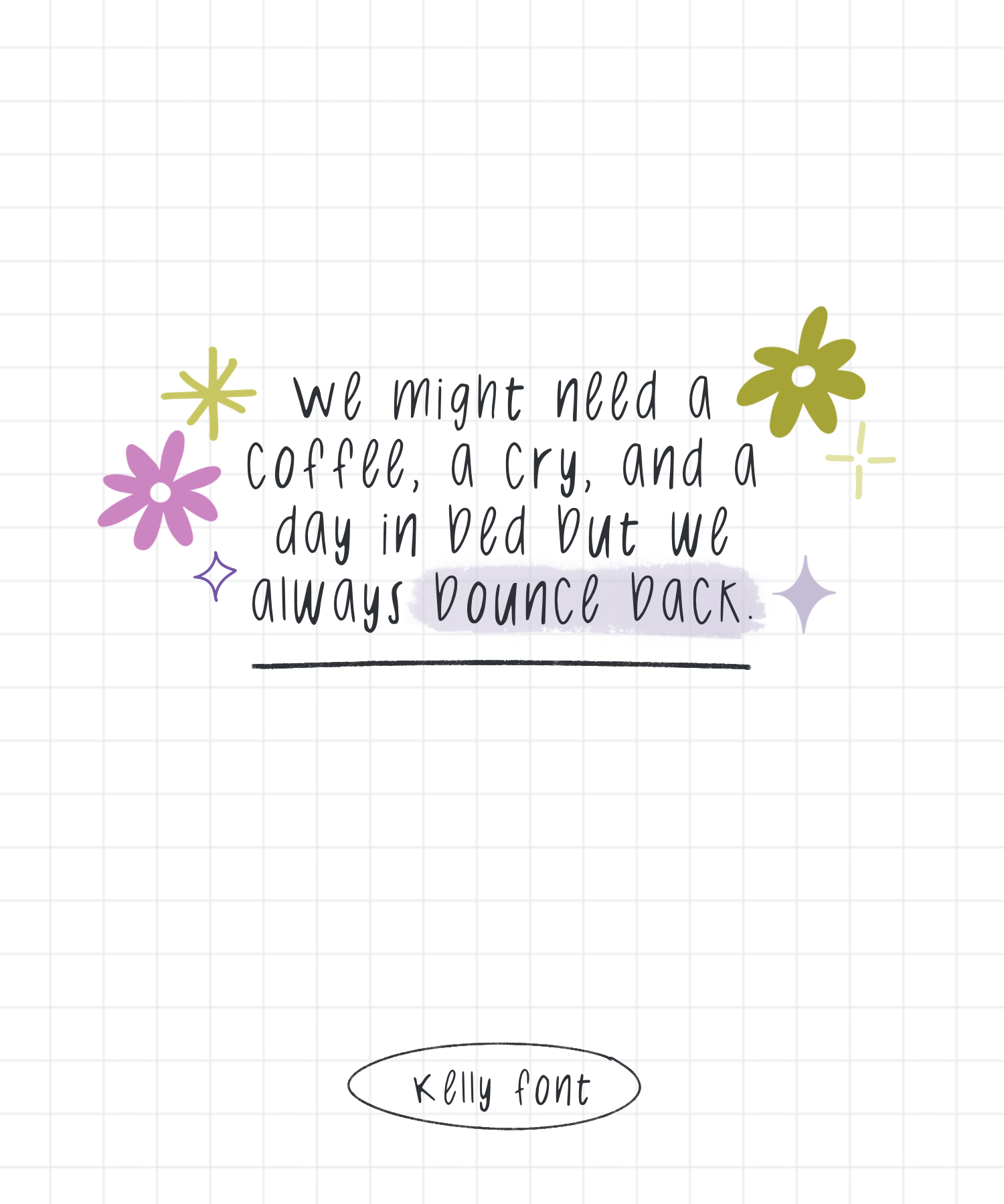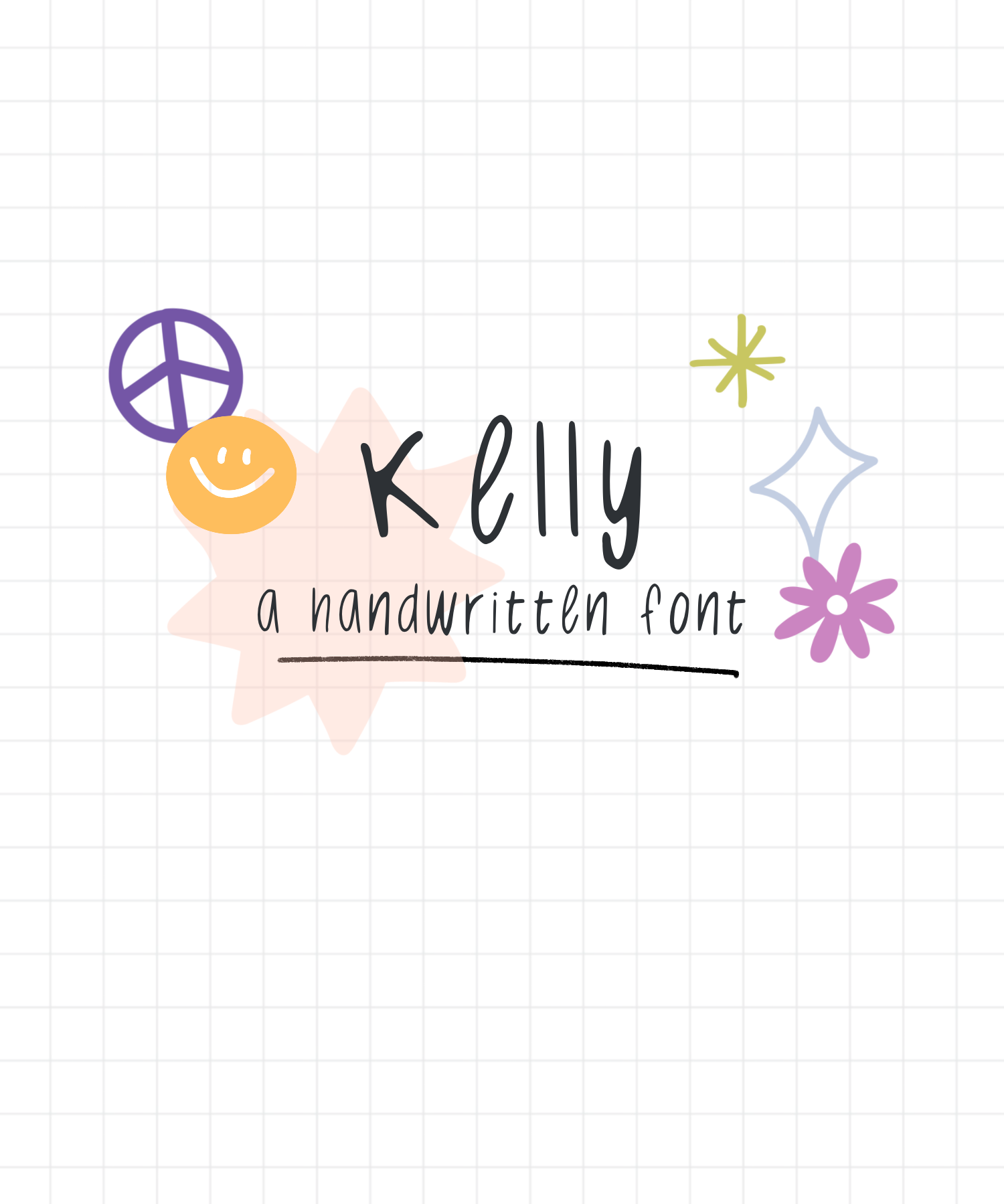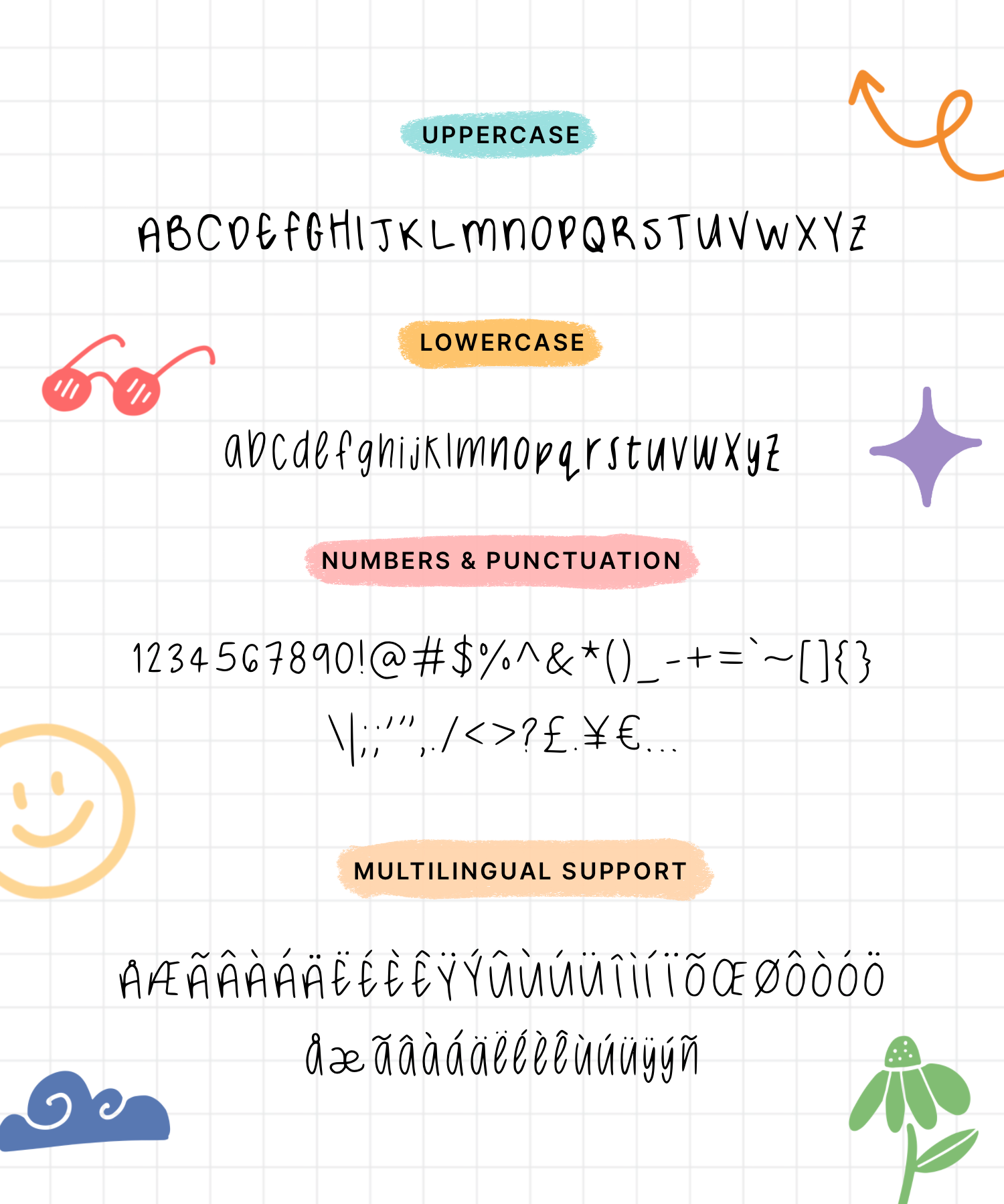
Fuente Kelly
Esta fuente está adorablemente escrita a mano y es perfecta para tomar notas o títulos. Ideal para agregar a tus proyectos Cricut o usar dentro de tus agendas digitales interactivas.